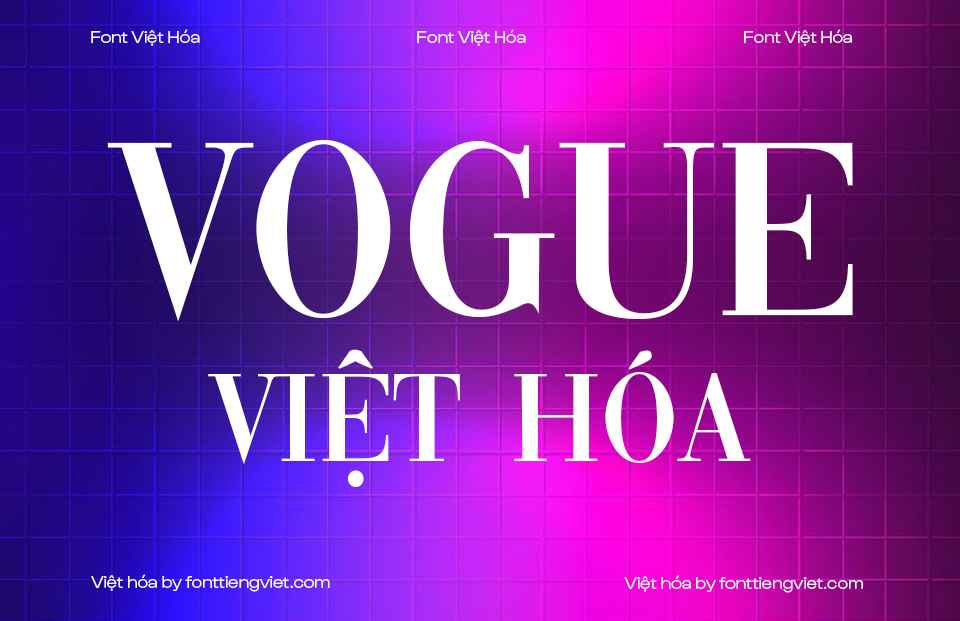
Font Việt hóa 1FTV VIP Vogue
Giới thiệu về bộ Font Việt hóa 1FTV VIP Vogue dành cho sáng tạo
Trong thế giới đồ họa hiện đại, việc lựa chọn một bộ Font Miễn Phí chất lượng luôn là ưu tiên hàng đầu của các nhà thiết kế trẻ. Đặc biệt, đối với những dự án mang tính thẩm mỹ cao như bìa tạp chí, lookbook thời trang hay bộ nhận diện thương hiệu cao cấp, Font Việt hóa 1FTV VIP Vogue nổi lên như một sự lựa chọn hoàn hảo. Đây là một phông chữ thuộc phong cách Serif tân cổ điển, mang đậm nét thanh lịch, sang trọng và đầy quyền lực, lấy cảm hứng từ các tiêu đề của những tạp chí danh tiếng nhất thế giới. Sự kết hợp giữa những đường nét thanh mảnh và các nét dày tương phản mạnh mẽ đã giúp bộ chữ này tạo nên một diện mạo vô cùng chuyên nghiệp và thu hút ngay từ cái nhìn đầu tiên.
Tại sao bạn nên sở hữu Font Việt hóa 1FTV VIP Vogue?
Lý do đầu tiên khiến Font Việt hóa 1FTV VIP Vogue trở nên phổ biến chính là khả năng hiển thị tiếng Việt trọn vẹn và mượt mà. Đội ngũ 1FTV đã thực hiện tinh chỉnh kỹ lưỡng các dấu câu để đảm bảo chúng không bị chồng chéo hay làm mất đi vẻ đẹp nguyên bản của thiết kế. Điều này cực kỳ quan trọng đối với các bạn học sinh, sinh viên đang thực hiện các bài thuyết trình hoặc thiết kế Portfolio cá nhân. Bên cạnh đó, bộ font này còn sở hữu các ký tự thay thế đa dạng, cho phép người dùng tùy biến linh hoạt để tạo ra những tiêu đề độc bản, không bị trùng lặp với bất kỳ ai khác trên thị trường sáng tạo hiện nay.
Ứng dụng thực tế của Font Việt hóa 1FTV VIP Vogue trong đời sống
Với phong cách đặc trưng, bộ phông chữ này thường được ứng dụng trong các không gian nghệ thuật và truyền thông đòi hỏi sự tinh tế. Bạn có thể dễ dàng bắt gặp chúng trên các tấm áp phích quảng cáo mỹ phẩm, thiệp mời sự kiện sang trọng hoặc tiêu đề của các trang web thời trang. Đối với môi trường học đường, các bạn có thể sử dụng font chữ này để làm nổi bật các đề mục lớn trong các tờ báo tường hoặc bìa sách kỷ yếu, giúp sản phẩm trở nên bắt mắt và chuyên nghiệp hơn hẳn so với các phông chữ mặc định thông thường. Sự linh hoạt của nó giúp người dùng dễ dàng phối hợp với các kiểu chữ không chân khác để tạo ra sự cân bằng cho thị giác.
Lưu ý khi sử dụng Font Việt hóa 1FTV VIP Vogue hiệu quả
Để phát huy tối đa vẻ đẹp của Font Việt hóa 1FTV VIP Vogue, bạn nên sử dụng nó cho các đoạn văn bản ngắn hoặc tiêu đề lớn thay vì các đoạn văn bản dài. Do tính tương phản cao giữa các nét, việc để cỡ chữ quá nhỏ có thể gây khó đọc trên các thiết bị màn hình độ phân giải thấp. Một mẹo nhỏ cho các bạn là hãy tăng khoảng cách giữa các chữ cái (tracking) một chút khi sử dụng in hoa hoàn toàn để tạo cảm giác thoáng đãng và đẳng cấp hơn. Việc kết hợp màu sắc trang nhã như vàng đồng, đen tuyền hoặc trắng tinh khôi cũng sẽ giúp bộ chữ này tỏa sáng rực rỡ trong các bản thiết kế của bạn.